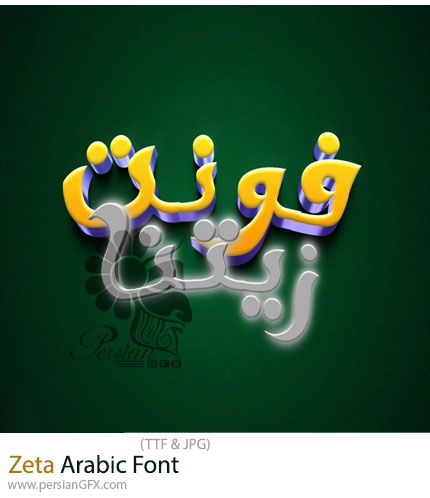
در این بخش شاهد فونت عربی به نام زیتنا می باشید که با فرمت TTF بر روی سایت برای دانلود قرار گرفته است. فونت Zeta یک قلم حرفهای و مدرن است که برای تایپ متون عربی با ظاهری زیبا، خوانا و کاربردی طراحی شده است. این فونت ترکیبی هوشمندانه از سنت خوشنویسی عربی با طراحی گرافیکی معاصر را ارائه میدهد و میتواند در انواع پروژههای چاپی و دیجیتال مورد استفاده قرار گیرد، از جمله طراحی لوگو، پوستر، جلد کتاب، رابط کاربری وب و اپلیکیشن، محتوای شبکههای اجتماعی و برندینگ. Zeta با هدف ایجاد تعادل بین زیباییشناسی سنتی عربی و نیازهای طراحی معاصر ساخته شده است. این فونت دارای ساختاری است که از نظر چیدمان حروف، ارتفاع، فاصلهگذاری و ضخامت خطوط کاملاً هماهنگ و متناسب است. حروف دارای فرمهایی نرم و روان هستند، بدون زوائد اضافی، که باعث سهولت در خواندن و استفاده در فضاهای متنوع میشود. این فونت یک انتخاب حرفهای برای کسانی است که به دنبال تلفیق زیبایی سنتی عربی با فرمهای مدرن هستند. این فونت با تنوع وزنی، پشتیبانی کامل زبانی، طراحی هماهنگ و ظاهر شیک، گزینهای عالی برای پروژههای تبلیغاتی، رسانهای و فرهنگی به شمار میآید.
کاربردهای فونت:
- طراحی لوگو و هویت بصری برندهای عربزبان یا فارسیزبان
- پوسترهای تبلیغاتی، بنرها، جلد کتاب و مجلات
- تولید محتوا برای شبکههای اجتماعی، بهویژه محتوای تصویری و موشنگرافیک
- طراحی رابط کاربری (UI) برای وبسایتها و اپلیکیشنهای موبایل
- استفاده در پروژههای فرهنگی، آموزشی و رسانهای